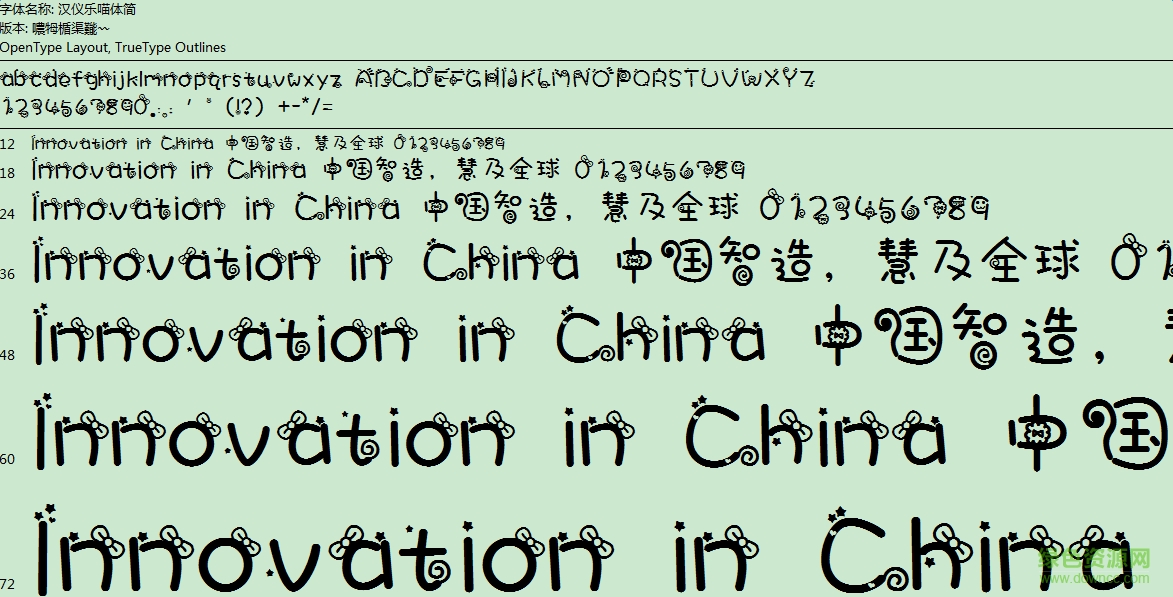
漢儀樂(lè)喵體簡(jiǎn)
漢儀樂(lè)喵體簡(jiǎn)字體是一款非常好用的漢儀字體,字體略帶圓潤(rùn),非常的俏皮可愛(ài),字體還有蝴蝶結(jié),小星星等圖案,非常的具有少女心,歡迎喜愛(ài)的朋友到綠色資源網(wǎng)下載使用!
是漢儀出品的字體,用途廣泛,文字排版、海報(bào)設(shè)計(jì)、藝術(shù)設(shè)計(jì)、廣告設(shè)計(jì)等方面都可以使用。
漢儀樂(lè)喵體簡(jiǎn)字體是一款非??蓯?ài)的卡通字體,帶有喵咪的屬性,非常生動(dòng)有趣,活潑。